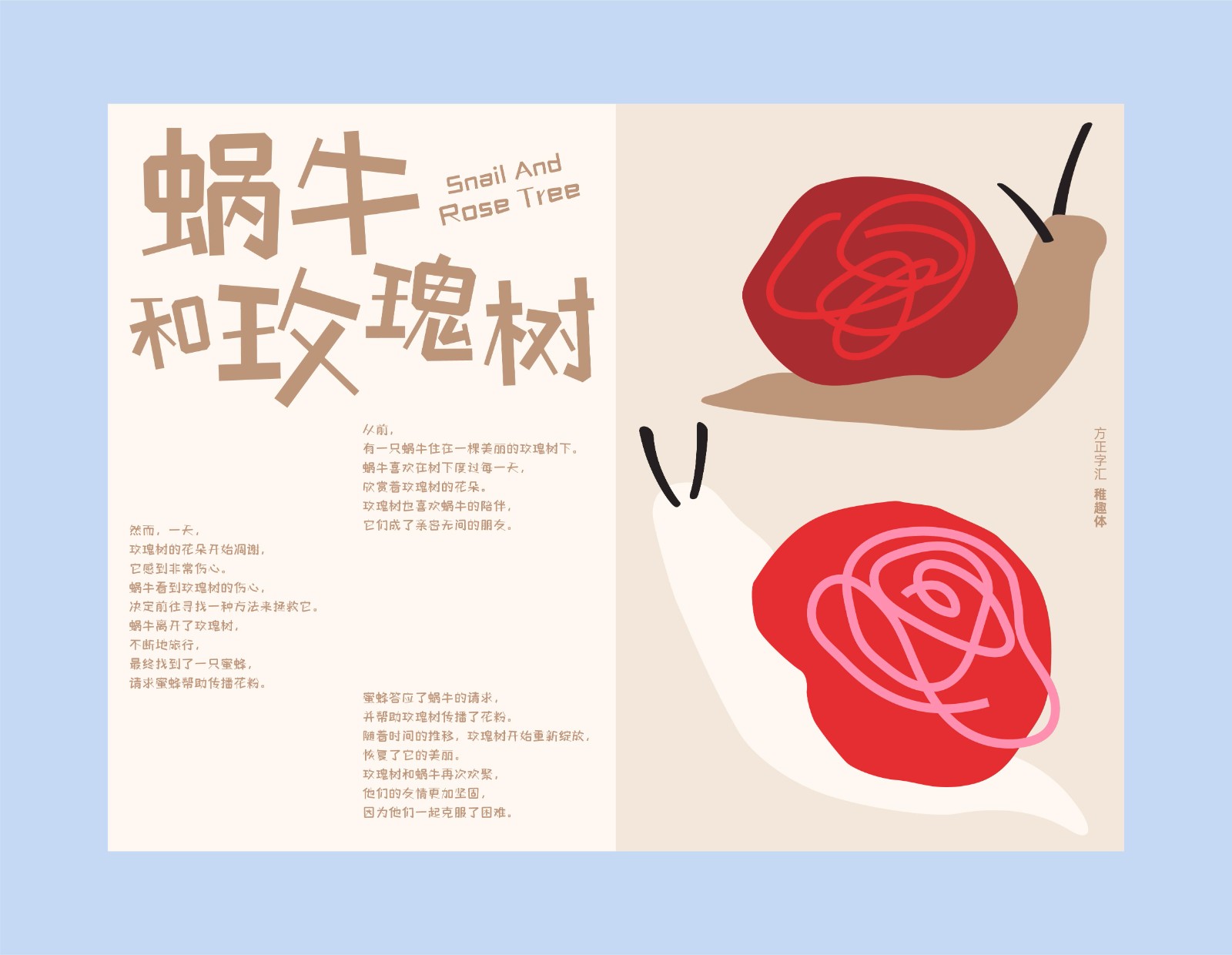
方正字汇-稚趣体
字体品牌: 方正字汇 设计师:赖灿伟 字体分类:创意字体 字体属性:精品字 字符集:大陆简体(GB2312-80) 发布时间: 2023
这款字体由粗细不一的线条搭配组合而成,笔画之间辅以随性自由的曲线以及圆点,使文字充满活力和趣味性。字里行间仿佛透露着一股孩提的稚趣,错落自然的排版呈现出不规则的节奏感。